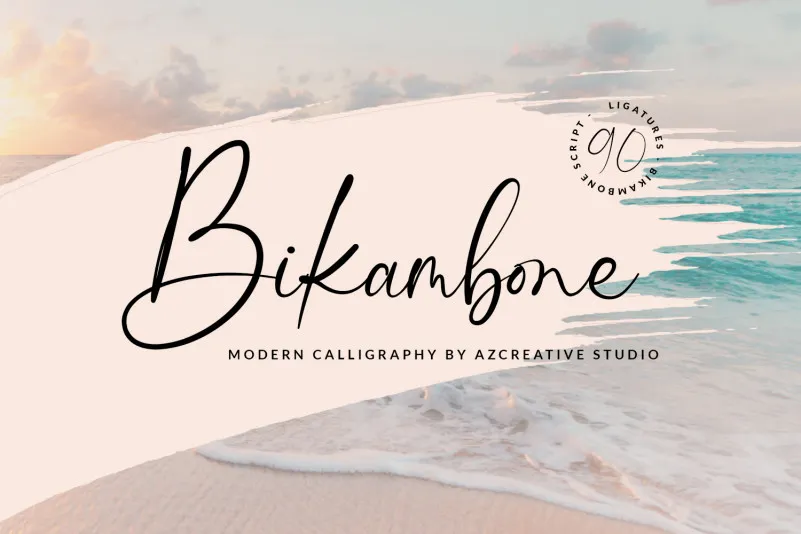
Esta fonte se apresenta com uma elegância e encanto únicos, inspirando-se na arte sagrada das escritas manuscritas. Ela é perfeita para designers buscando incorporar um toque de elegância clássica às suas criações digitais. A ‘Bikambone Font’ possui uma linha de base variável que permite diferentes posições, além de linhas suaves e belos caracteres que oferecem várias alternativas incrivelmente estilizadas. Além disso, a fonte PUA (Proprietary Unicode Association) permitiu que designers acessassem facilmente todos os detalhes encantadores, como as sobrancelhas e ligaduras únicas de uma maneira intuitiva. Com um leque amplo de recursos especiais, esta fonte também permite a inclusão de alternativas de caracteres para aqueles desejando maior versatilidade ou quando há necessidades específicas. Com a ‘Bikambone Font’, designers e criativos têm o poder de criar trabalhos que brilham tanto no papel quanto digitalmente, oferecendo uma combinação única de elegância e personalização.